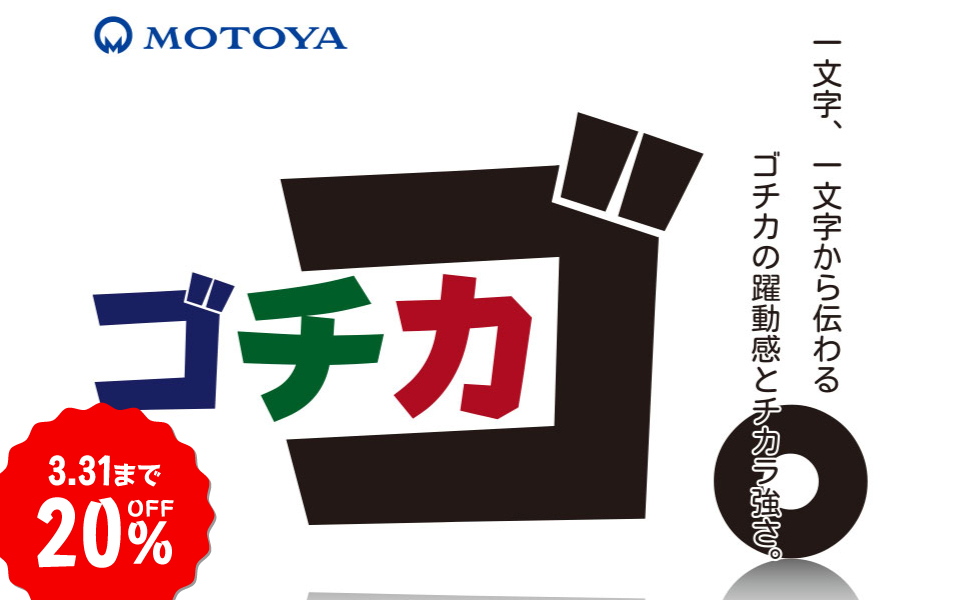
力強さと動躍感を抑えた「モトヤゴチカ」
躍動感とチカラ強さを感じさせる書体「モトヤゴチカ」
「モトヤゴチカ」は、ゴシック体をベースに、横線やハライに筆文字の勢いを加えた強い書体です。仮名デザインは、運筆の美しさを重視しながら、迫力を持たせています。
モトヤゴチカとは
モトヤゴチカは、ゴシック体をベースとし横線やハライに筆文字の勢いを表現しており、躍動感とチカラ強さを感じさせる書体です。また、仮名のデザインは、運筆の流れの美しさや柔らかさを保ちながらも、チカラ強さを加えており迫力のある表情を持っています。
ゴチカが与える躍動感とチカラ強さは、カタログやチラシのタイトルやキャッチコピーで威力を発揮するのはもちろんのこと、テレビテロップ・ゲームやWeb等のデジタルコンテンツにも最適です。様々な場面で文章表現に迫力とインパクトを与えることが可能な書体です。
使用例
モトヤゴチカがもたらす躍動感と力強さは、カタログやチラシのタイトルやキャッチコピーで威力を発揮します。また、テレビテロップ、ゲーム、動画、Webなどのデジタルコンテンツにも最適です。さまざまな場面で、表現に迫力とインパクトを与えることができます。
▼ カタログやチラシのタイトルやキャッチコピーに最適
▼ 販促用のPOP広告やチラシに使うと、視認性の高いデザインに仕上がります
書体見本
モトヤゴチカ4
モトヤゴチカ6
モトヤゴチカ8